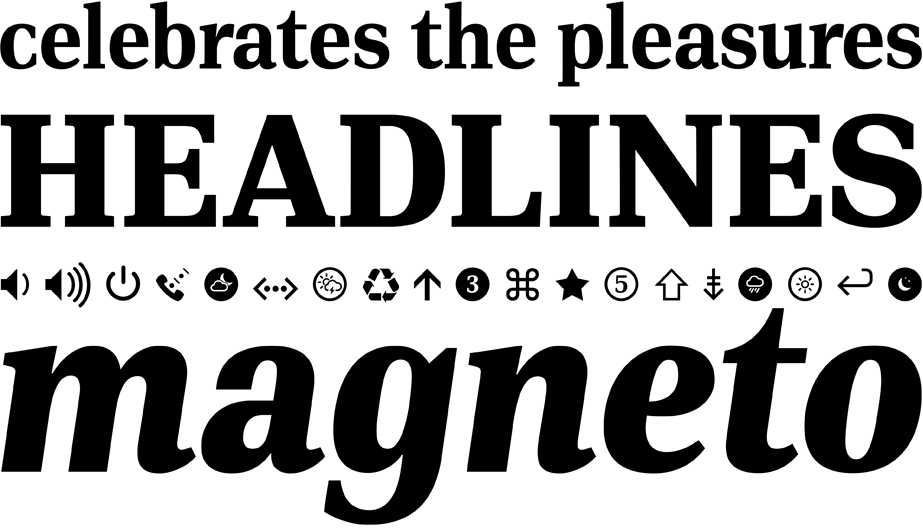
Passende Schmuckschrift zu DIN light?
hat jemand einen Tipp für eine Schmuckschrift, die sich gut zur DIN light, die für die allgemeinen Texte verwendet wird, kombinieren lässt? Ziel ist es, mit der Schmuckschrift etwas aus dem Rahmen zu fallen sowie Dynamik und Kreativität zu vermitteln. "Loved by the king" gefiel uns auf den ersten Blick ganz gut - die Kombi mit DIN light war dann allerdings nicht so überzeugend ;-) Freue mich auf eure Tipps.
Wenn Du magst, dann schau Dir doch mal die Liste der Handschriften und der Kreideschriften hier im Forum an, vielleicht ist da etwas für Dich dabei? Ansonsten gibt es gut gestaltete Schriftfamilien wie Festivo, Charcuterie oder auch Catalina, die jede Menge Schriften in handgezeichnetem Duktus enthalten. Bei den kostenlosen oder jedenfalls preiswerten Schriften könntest Du Dir Armatic und Sketch Block anschauen.
Ansonsten wäre die DIN Next Slab vielleicht noch eine Idee?
… oder die neue DIN Serif von Parachute, wenn man gerade keine FF Meta Serif zur Hand hat. ;-)
Wobei Du damit nicht wirklich »aus dem Rahmen fällst« oder sonderlich viel »Dynamik und Kreativität vermittelst«.